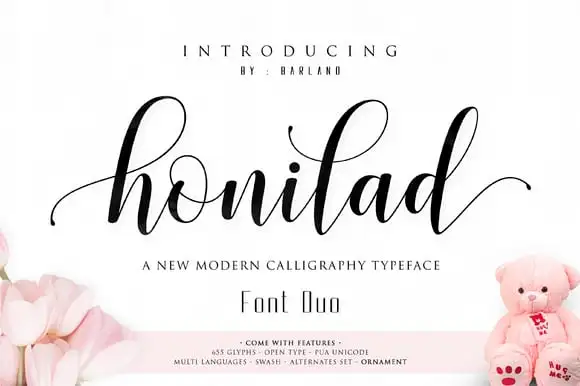
A Honilad Calligraphy Typeface é uma criação inovadora do designer Barland, que combina elementos clássicos com modernidade única para formar um estilo distintivo e singular. Esta fonte não é apenas uma adaptação convencional, mas sim uma mistura sofisticada de letras antigos e linhas atuais, trazendo uma personalidade vibrante à qualquer trabalho onde ela seja aplicada. Suas linhas oscilam com elegância, evocando um movimento fluido da dança das letras, enquanto mantêm-se limpas e simples, proporcionando um desenho perfeito para estilos de escrita tipográfica ou outros trabalhos gráficos que buscam uma sensação única. Ideal tanto para aqueles buscando um pouco de classe clássica quanto aqueles procurando algo moderno e inovador em suas fontes de design, a Honilad Calligraphy Typeface é o ideal escolha para criar uma atmosfera envolvente e natural em seu próximo projeto.
Designer: Barland